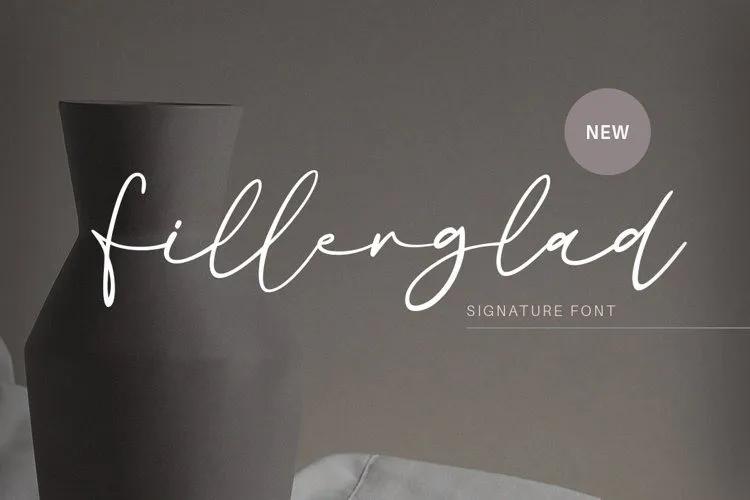
A ‘Fillerglad Font’ é uma elegante fonte à mão livre projetada por Letterhend Studio que se destaca entre outras serifadas modernas. Ela traz ao público um estilo casual porém cuidadosamente perfeito, ideal para aplicar em diversas formas formais como logotipos, convites e etiquetas, livros, revistas ou cartões de aniversário, embalagens, maquiagem, estaçãoários, novels, selos ou até mesmo materiais publicitários. A fonte é perfeitamente versátil para qualquer tipo de aplicação visual, tornando-a uma escolha valiosa para designers e criadores de arte digitais. Seja você um iniciante ou um profissional da indústria, a ‘Fillerglad Font’ oferece uma gama incrível de possibilidades que vão do simples ao complexo em qualquer projeto gráfico.